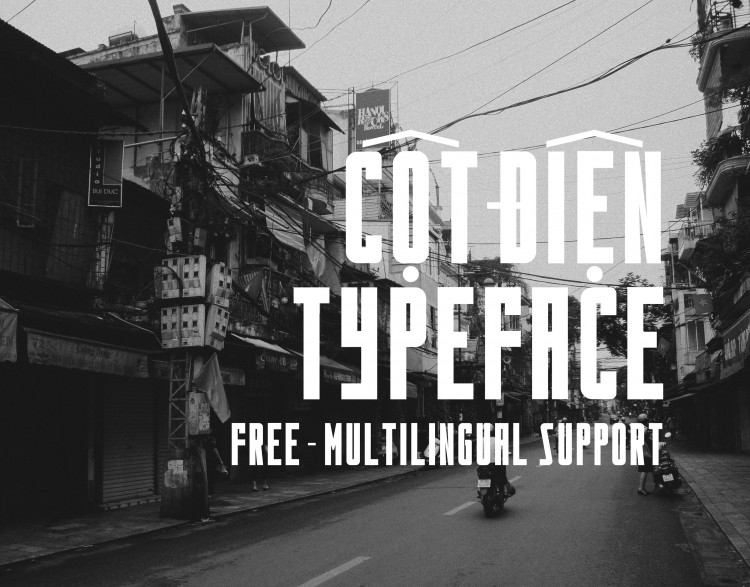
Font việt hoá Cotdien Typeface – Bộ font chữ hoài cổ độc đáo cho thiết kế
Trong thế giới đồ họa hiện đại, việc tìm kiếm một bộ Font Chữ mang đậm hơi thở hoài cổ nhưng vẫn đảm bảo tính ứng dụng cao là điều không hề dễ dàng. Font việt hoá Cotdien Typeface chính là giải pháp hoàn hảo cho những ai yêu mến phong cách Retro và Vintage. Được lấy cảm hứng từ những tấm biển quảng cáo vẽ tay tại Việt Nam vào những thập niên trước, bộ font này mang đến một cảm giác gần gũi, mộc mạc và vô cùng tinh tế cho mọi tác phẩm nghệ thuật.
Đặc điểm nổi bật của Font việt hoá Cotdien Typeface
Thiết kế mang đậm dấu ấn thời gian
Font việt hoá Cotdien Typeface nổi bật với những đường nét góc cạnh, mạnh mẽ nhưng không kém phần uyển chuyển. Kiểu dáng chữ cái gợi nhớ đến vẻ đẹp của Sài Gòn xưa, giúp các bạn học sinh và nhà thiết kế dễ dàng tái hiện lại không gian văn hóa truyền thống. Sự kết hợp giữa yếu tố cổ điển và kỹ thuật số hiện đại giúp bộ font này trở nên đa năng hơn trong nhiều tình huống khác nhau.
Khả năng tương thích và ứng dụng đa dạng
Nhờ quá trình việt hóa tỉ mỉ, các dấu câu và ký tự đặc biệt trong tiếng Việt được xử lý mượt mà, không xảy ra lỗi hiển thị. Bạn có thể sử dụng bộ font này để làm tiêu đề báo tường, thiết kế bìa sách, poster sự kiện trường học hay thậm chí là các dự án truyền thông trên mạng xã hội. Sự rõ ràng và cá tính của nó giúp thông điệp truyền tải trở nên ấn tượng hơn đối với người xem.
Cách sử dụng Font việt hoá Cotdien Typeface hiệu quả
Để phát huy tối đa vẻ đẹp của bộ font, bạn nên kết hợp với những tông màu trầm ấm như vàng nghệ, nâu đất hoặc đỏ đô. Việc căn chỉnh khoảng cách chữ hợp lý cũng giúp đoạn văn bản trở nên dễ đọc và chuyên nghiệp hơn. Đây chắc chắn là công cụ không thể thiếu trong kho tài liệu sáng tạo của bạn.